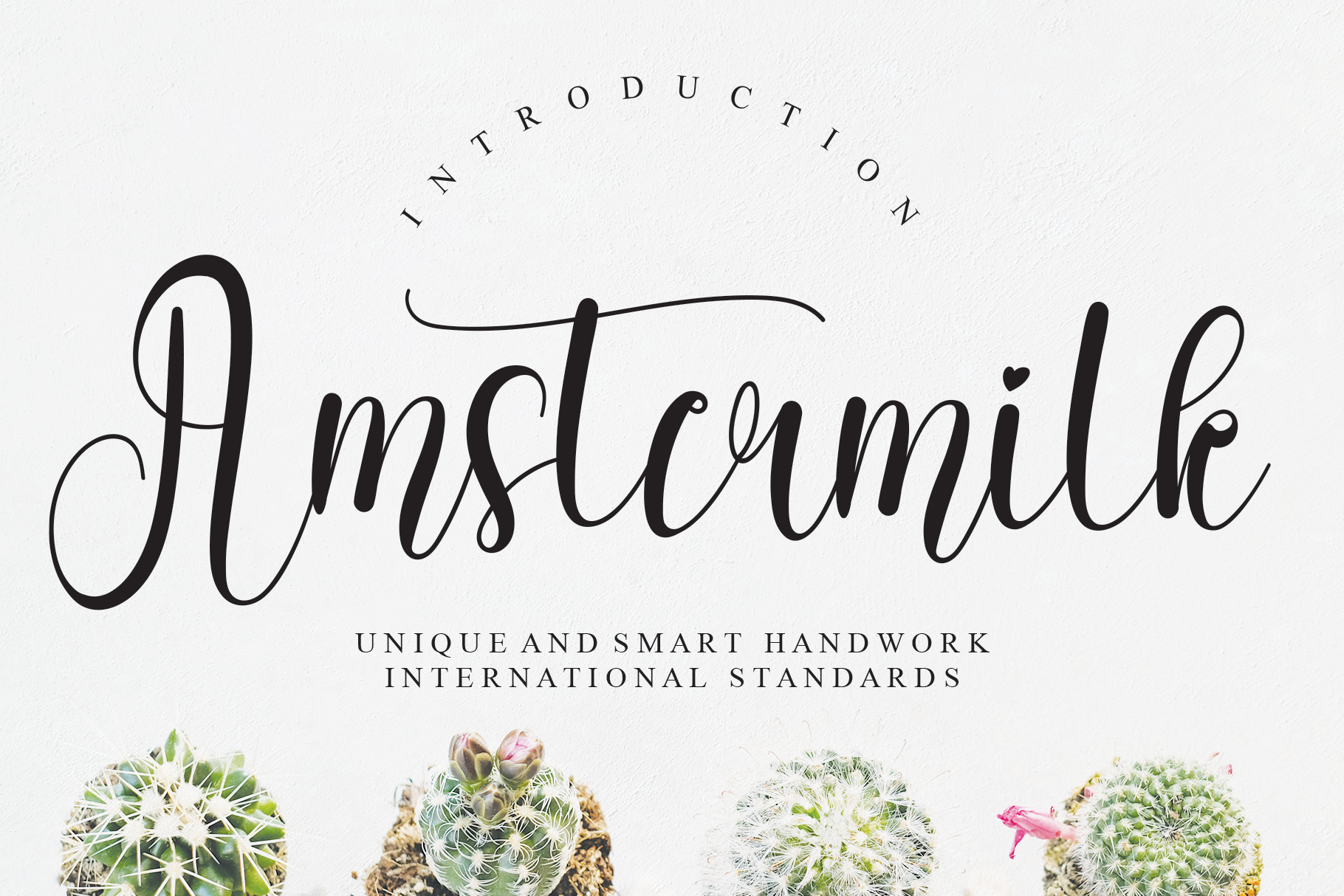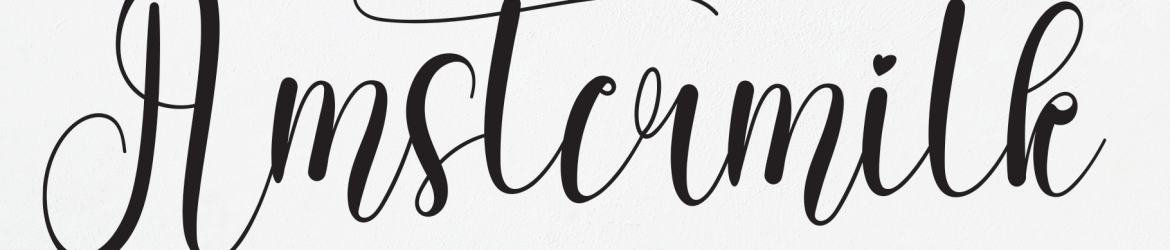
A Amstermilk Font é uma deliciosa mão-de-videira criada pelo talentoso designer creativeletter para experiências memoráveis em projetos variados. Seja você construindo um projeto de logotipo social, adesivo de aniversário, embalagem de produto ou mesmo um cartaz para o seu espaço comercial. A Amstermilk é a escolha perfeita para incorporar uma pitada única e autêntica à sua criação. Especialmente projetada para wall displays, convites de casamento, logos de mídia social e até mesmo logotipos de publicidade, você pode explorar a variedade de ambientes onde essa fonte é perfeitamente adaptável. Suave, fluida e cheia de personalidade, a Amstermilk vem para adicionar um toque único e autêntico aos mais variados projetos que valorizam a escrita manuscrita.